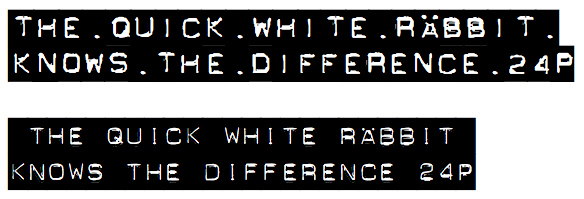
Büro Beschrifter / Labeler
ich suche dioe Schfift, die aussieht wie die der alten Büro Berschiftungsgeräte, dei so einen dünnen Klebestreifen mit Buchstaben ausspucken. Es sieht aus wie in Plastik gestanzt.
Gibts aber auch in besserer Qualität (unteres Beispiel) unter den FontFont Instant Types.
Ist von Just van Rossum und heißt FF Dynamoe (Das E am Ende nicht vergessen, denn Dynamo gibts bei E+F!
Ein ähnlicher Font mit anderer Anmutung ist Chromosome Heavy:
Die muss man aber weiß mit einem schwarzen Balken setzen, ich glaube, die gibt es nicht negativ wie die Dymo-Streifen.